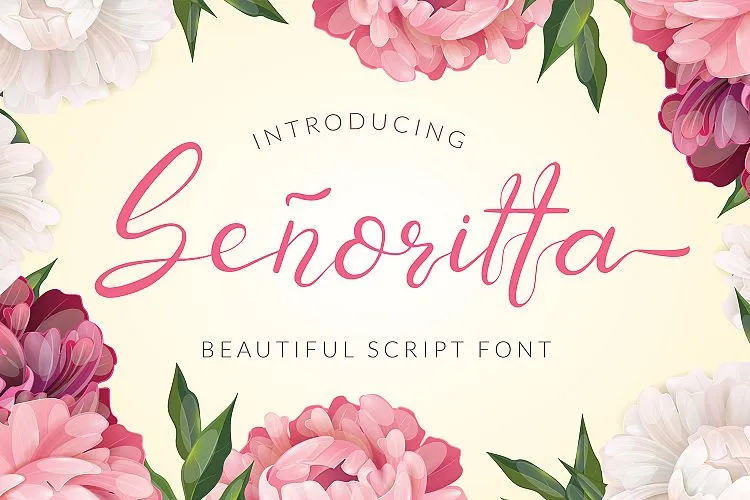
Senoritta Script Font – Download Grátis
A Senoritta Script Font é uma bela fonte de script que se destacará em projetos variados no campo do design gráfico. Seja para criações de logotipos e identidade visual, ilustrações de embalagens de produtos ou até mesmo para designs de capas de livros e cartões promocionais, a Senoritta Script será uma escolha inegável. Suave e elegante, essa fonte é perfeita para aplicar um toque personalizado e autêntico em todas as suas criações. Além disso, ela também se adequa à decoração de ambientes através de projetos como cartões de convite, cardapios de restaurantes ou mesmo sobrepostas únicas para fotos. Seja onde você a use, a Senoritta Script criará um padrão único em seu trabalho, tornando cada projeto não apenas individualmente autêntico, mas também repleto de encanto e sofisticação. Não importa o tipo de projeto que esteja no horizonte, a Senhoritta Script está pronta para desempenhar seu papel com mestria.